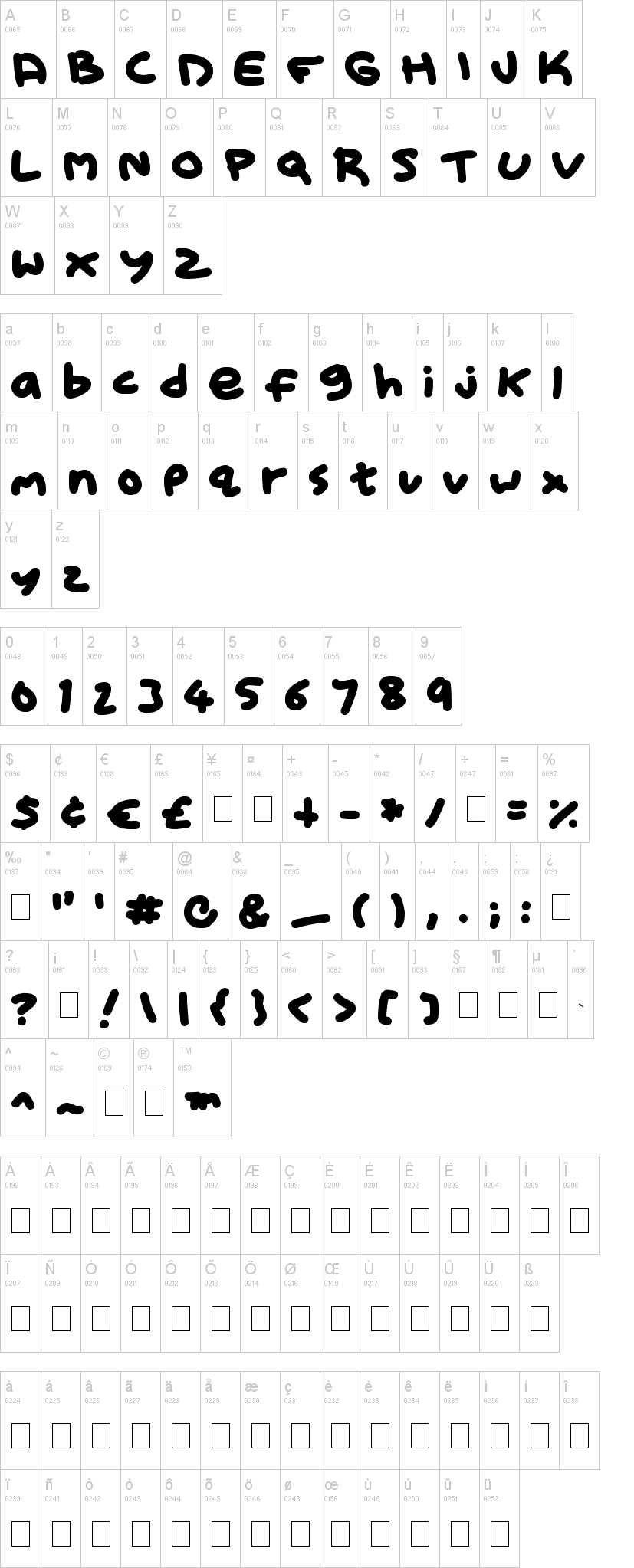
Kid Marker
Kid Marker 是一款拥有可爱外形的字体,其字形简单明了,具有清新可爱的外观,适合用于儿童类的文字排版,也可以用于其他类型的文字排版。它具有良好的可读性,可以使文字更加清晰明了,更容易被读者理解。此外,它还具有活泼的外观,可以为文字添加点缀,让文字更加有趣。
Kid Marker是一款非常不错的手写艺术字体,具有很好的视觉感,适合于文化类的宣传设计、商业类品牌的广告和产品包装设计以及个性化文字排版等较多场景。
Kid Marker字符映射图